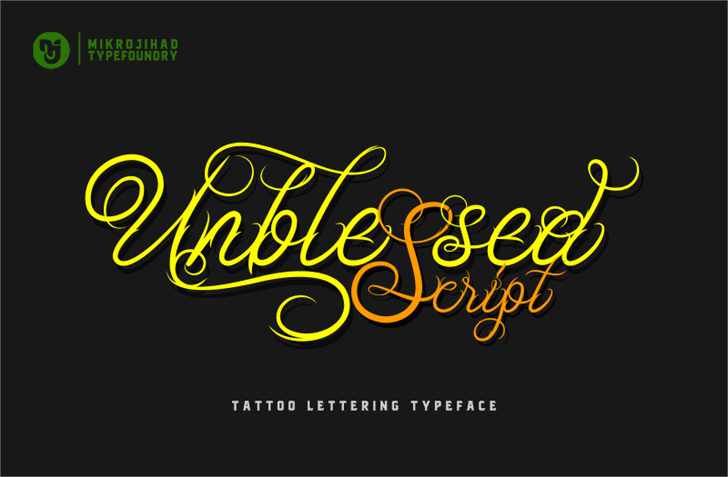
A Unblessed Script é uma fonte de escrita chinesa elaborada pelo designer Hamilton, trazendo nuances sutis que permitem explorar uma variedade impressionante de expressões e sentidos em seus textos. Esta fonte evoca a tranquilidade do xisto branco polido e o movimento da água no deserto, criando um contraste envolvente que se assemelha à delicada poesia chinesa. Com sua escrita fluida e harmoniosa, a Unblessed Script é perfeita para criar letras legíveis e arredondadas, ideal para gráficos de design editorial, revistas ou websites, onde o destaque do texto se assemelha ao deslizamento suave da água sobre pedra. Sua elegância e sutileza tornam a Unblessed Script uma escolha natural e convidativa para qualquer designer em busca de uma fonte que transcende as normas convencionais, oferecendo um toque único que ilumina o texto sem perder sua função essencial.